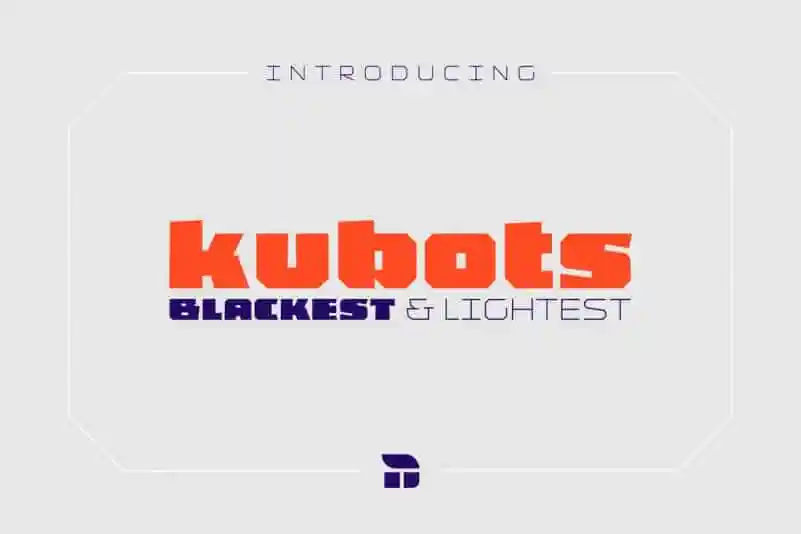
Kubots Display Font – Download Grátis
A Kubots Display Font é uma tipografia sans-serif que inspira-se nos cartazes de loja tradicionais de frutas e verduras dos anos 70 e início dos 80. Inspirada em estabelecimentos populares, como as delis, a fonte apresenta linhas retas e um design experimental que não se preocupa com curvas suaves, mas sim com formas interessantes e contrastes únicos tanto no papel quanto na tela. Essencial para quem busca uma tipografia moderna e futurista, a Kubots Display oferece uma experiência visual única. Seu design é perfeito para estilos de marca criativos e visuais dinâmicos que valorizam os elementos geométricos puros e o contraste de linhas retas contra formas mais fluidas em sua tipografia. Para designers amadores ou profissionais, a Kubots Display Font é uma escolha ideal, com um design moderno e vibrante capaz de destacar qualquer tipo de layout gráfico. Esta fonte de display é perfeitamente adaptável para criar visuais que vão desde as bordas das páginas da internet até o encarte de revistas ou os títulos de vídeos, garantindo uma experiência visual agradável tanto na impressão quanto no digital.